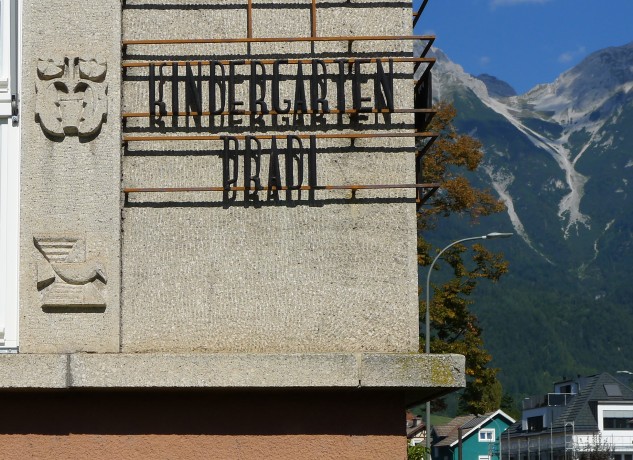
Kindergarten Pradl
Die Beschriftung am Kindergarten im Innsbrucker Stadtteil Pradl setzt den Stil des Bauwerks konsequent fort, das 1928 nach einem Entwurf von Theodor Prachensky entstanden ist. Ein schönes Beispiel der Tiroler Moderne. Filigrane Metallbuchstaben sind auf einem Stahlgitter mit Abstand zur Mauer montiert, das Gitter kehrt als Motiv auch im Inneren des Gebäudes wieder. Mit Schattenwurf ist die Schrift fast nur mehr als Muster wahrzunehmen – trotzdem, wunderbar charakteristisch und einzigartig. Der Schriftzug ist vermutlich eine freie Interpretation des Schriftgestalters (oder sogar des Architekten selbst; er war ja auch als genialer Plakatgestalter und Künstler bekannt Vorbilder könnte man im Konstruktivismus vermuten und interessant ist auch, dass ähnliche Formen von Typografen später wieder aufgegriffen und Schriften daraus erarbeitet wurden, wie zB die „Industria“ von Neville Brody oder Daniel Pallavins „ITC Anna“.
Innsbruck, Egerdachstraße